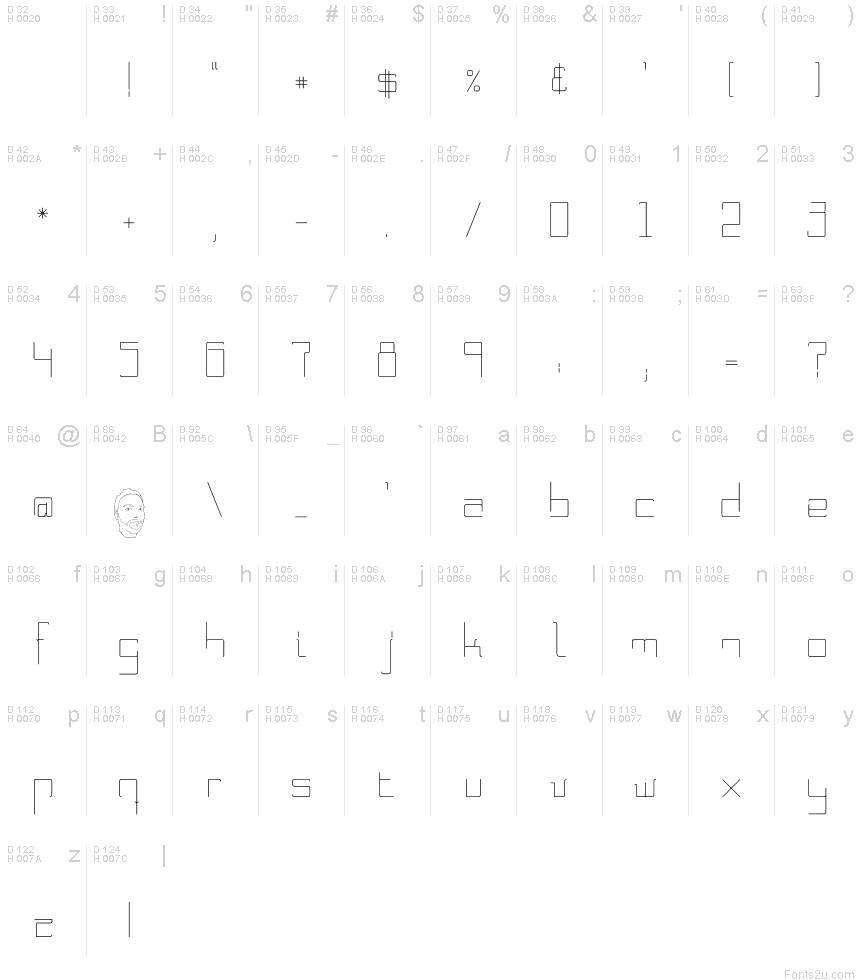
Nada von der Lagalga Foundry ist eine kostenlose Display-Schrift mit futuristischem, modernem Charakter, die durch abgerundete rechteckige Formen und offene, rahmenartige Striche definiert wird. Die wiederkehrende Geometrie verleiht ihr einen simplen, modularen Rhythmus, der eher an konstruierte Beschilderung als an Handschrift oder klassische Serifen erinnert.
Nada eignet sich hervorragend für Logos, Plakat-Titel, Sci-Fi-Verpackungen, Interface-Labels und Event-Grafiken, da ihre reduzierten Konturformen eine starke grafische Präsenz ohne überflüssige Details bieten. Diese kostenlose Schrift ist zudem ideal für Markenakzente und dekorative Überschriften, wenn Sie einen geometrischen, technischen Look suchen, der auch bei kurzen Texten für Konsistenz sorgt.